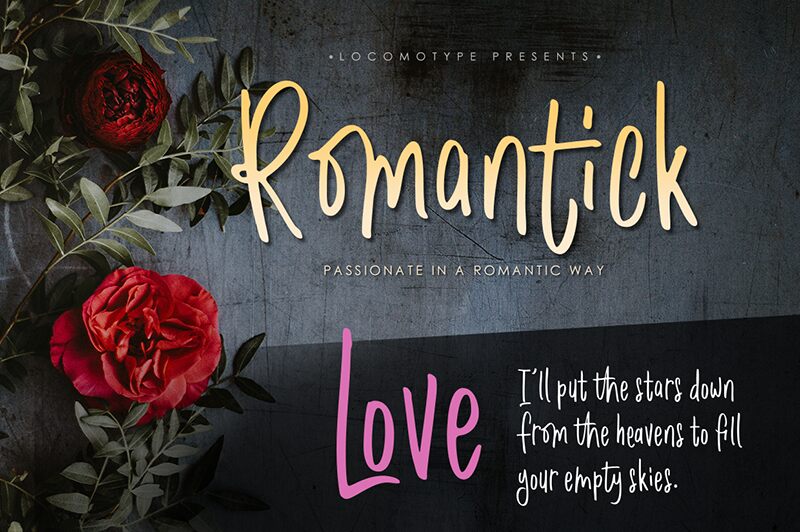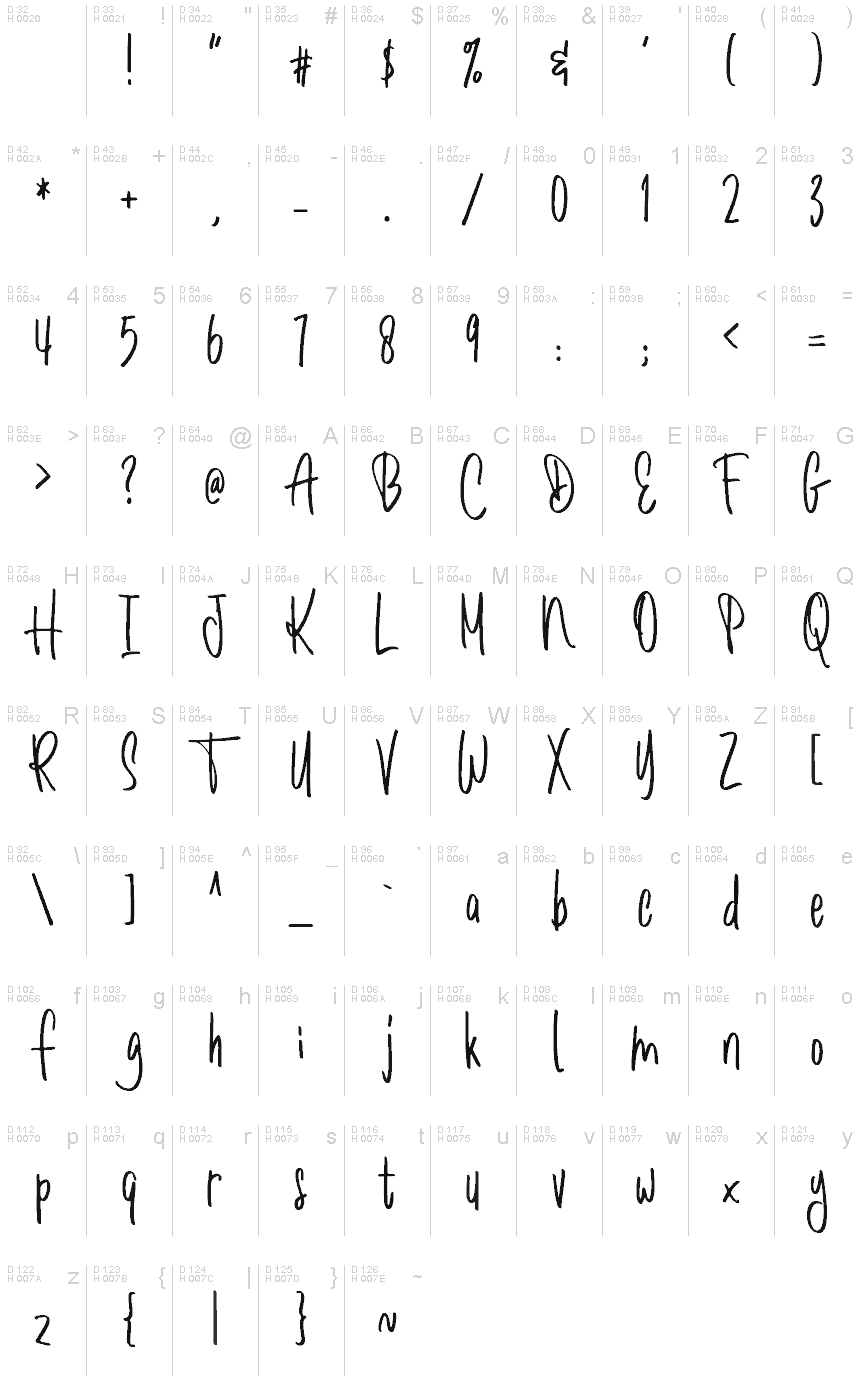
Romantick هو خط شبه مخطوطي (semi-script) مستوحى من الكتابة اليدوية بفرشاة دقيقة. يتميز بأسلوب بسيط وعفوي، ويحتوي على بعض الربط بين الحروف (ligatures) ليضفي على تصميماتك طابعاً شخصياً مميزاً. كما تمنحك الأحرف الإضافية في البدائل الأسلوبية خيارات أوسع لاستكشاف تصاميم جديدة.
يُعد Romantick مثالياً لتصميم دعوات الزفاف، والاقتباسات، والشعارات، والتغليف، وغيرها الكثير. والأهم من ذلك، يمكنك استخدام خط Romantick مجاناً للأغراض الشخصية والتجارية على حد سواء.
Romantick